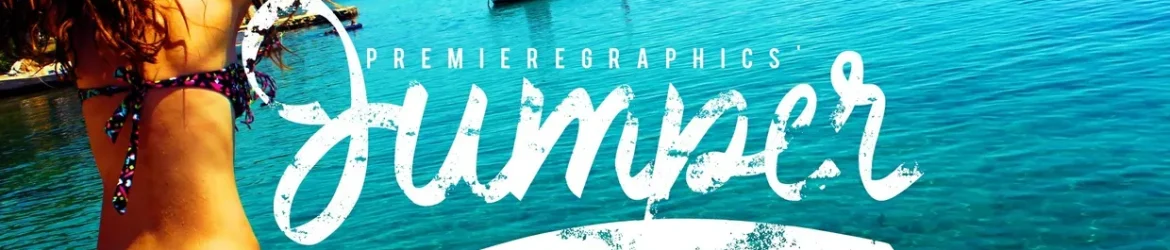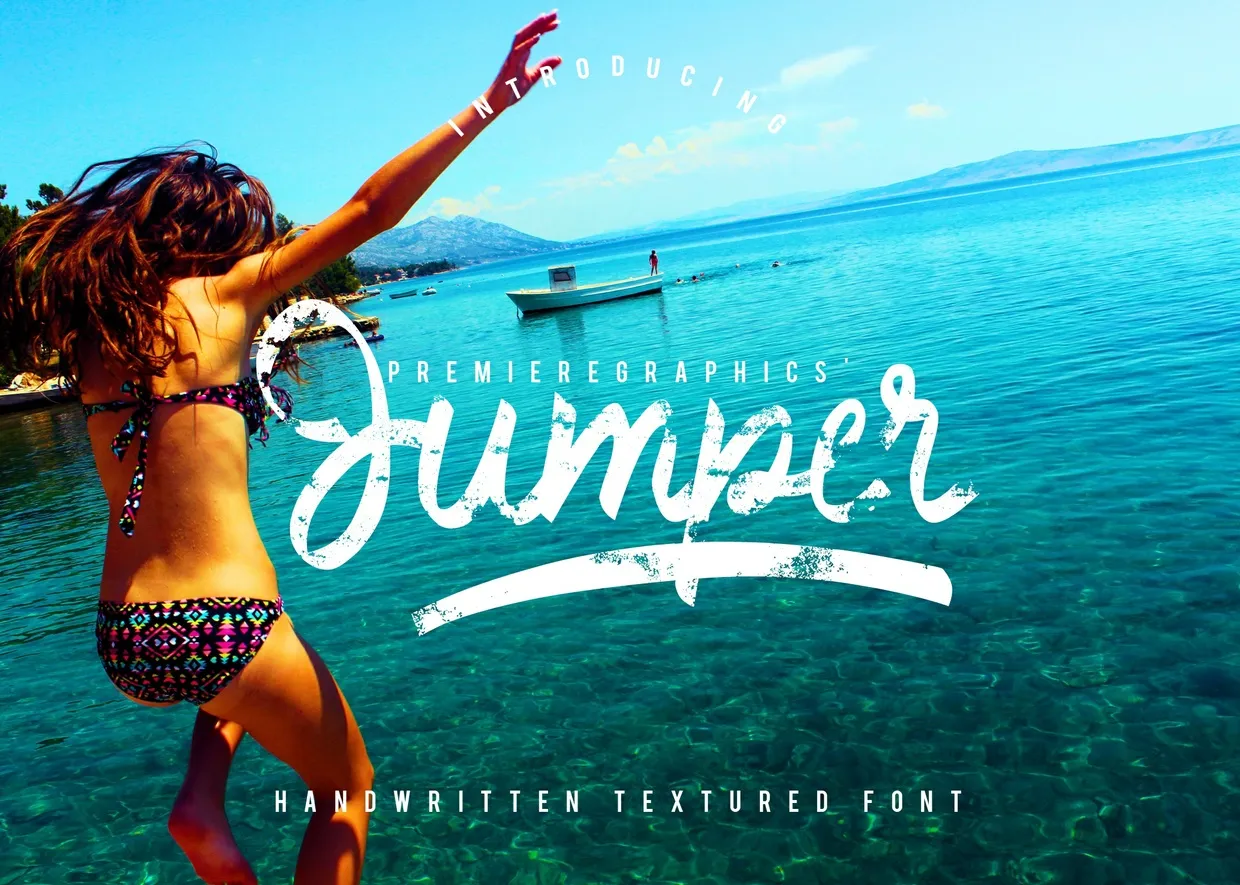
Jumper Handwritten Font – Fonte Grátis
Jumper Handwritten Font
Descubra a Jumper Handwritten Font, uma elegante e vibrante tipografia brush font criada pelo designer Hamilton. Esta fonte é mais do que simplesmente uma maneira de escrever; ela carrega consigo um ar único e sofisticado. Jumper foi projetada para capturar a essência da escrita manual com uma textura rica, dando-lhe uma aparência ainda mais robusta e inconfundível. Ideal tanto para designers de fotos quanto para blogueiros ou criadores de marca, a Jumper Handwritten se tornou o elemento ideal para um estilo visual moderno. Sujeitos como retratos em fotografias, letras bonitas nos blogs, logotipos e marcas pessoais, capas de livros ou bandas, todos encontram na Jumper uma fonte que combina perfeitamente com a essência do seu trabalho. Os recursos incluídos no pacote da fonte não deixam nada a desejar. Inclui traçados sobresselentes e caracteres únicos meticulosamente criados para oferecer ainda mais opções aos artistas digitais. A Jumper é o tipo de letra que vai adicionar profundidade ao seu projeto, trazendo um toque único com um estilo autêntico que ressoa no coração do design contemporâneo.